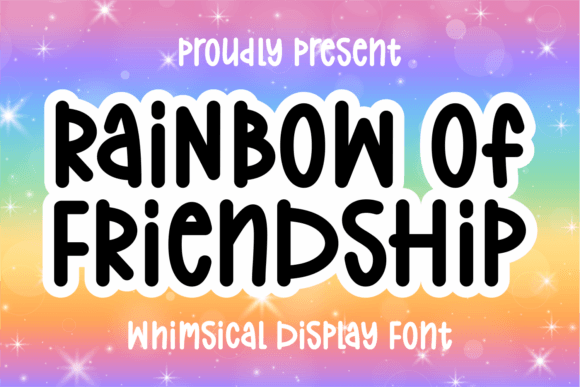
Rainbow of Friendship
找到合适的设计元素可能具有挑战性,但 Rainbow of Friendship 提供了一系列出色的藏品,可瞬间提升您的作品质量。
无论您是创建 POD(按需打印)产品、婚礼邀请函还是社交媒体图形,Rainbow of Friendship 都是理想的选择。